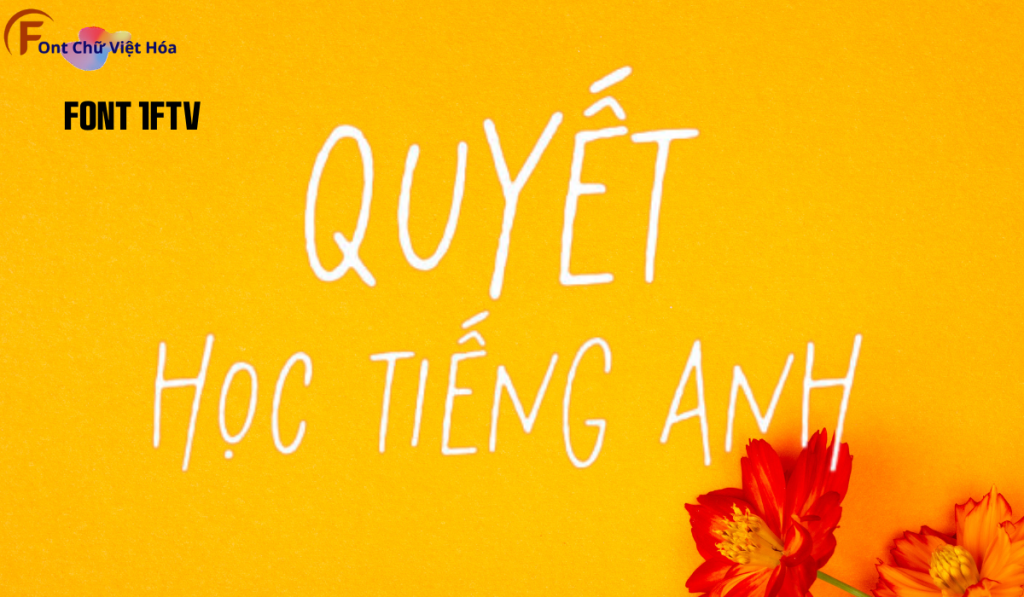
Font 1FTV English Speakers
Font 1FTV English Speakers là một font chữ độc đáo, thuộc bộ 1FTV, nổi bật với phong cách handwritten hiện đại và các đường nét mềm mại, tinh tế. Thiết kế của 1FTV English Speakers tập trung vào sự thanh lịch và dễ đọc, đặc biệt phù hợp cho các thiết kế đòi hỏi tính thẩm mỹ cao như poster, logo, và tiêu đề. Với tỷ lệ chữ cân đối và các đường nét rõ ràng, font này tạo ra ấn tượng thị giác mạnh mẽ và giúp tối ưu hóa không gian trong thiết kế. Font này cũng đã được Việt hóa, mang đến sự linh hoạt và tiện dụng cho các dự án thiết kế bằng tiếng Việt.